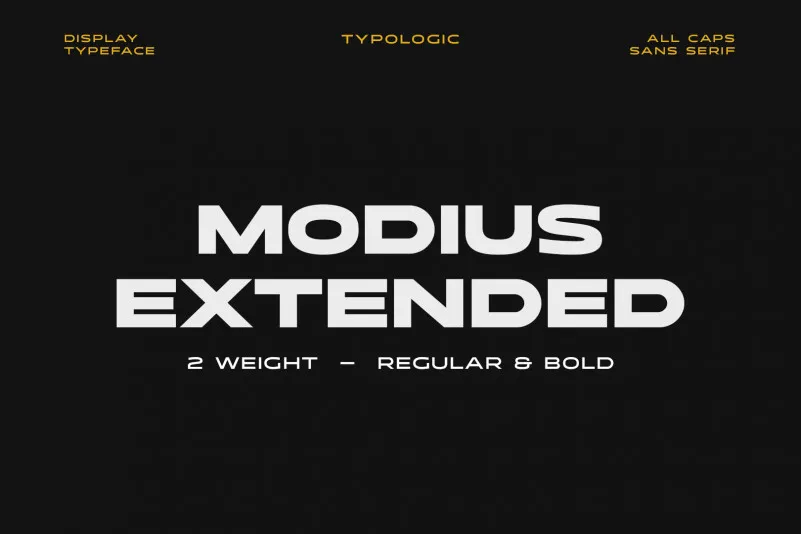
Introduzimos a Fonte Modius Extended, uma extensão personalizada que mescla agressividade com simplicidade. Inspirada no design moderno e urbano simples, essa fonte impressiona de forma clara e contundente quando usada como texto em destaque. Através do uso deste tipo customizado, você pode criar projetos visuais intrigantes e dinâmicos sem perder a elegância necessária para um design limpo e sofisticado. Sua simplicidade moderna faz com que seja uma escolha ótima para qualquer projeto de design que busque estabelecer seu ponto de vista ou comunicar sua mensagem de maneira clara e impactante. Modius Extended é a fonte perfeita para aqueles que querem combinar personalização com sofisticação em suas criações visuais, tornando-a uma escolha inegável tanto para projetos digitais quanto para impressão.
Designer: typologic